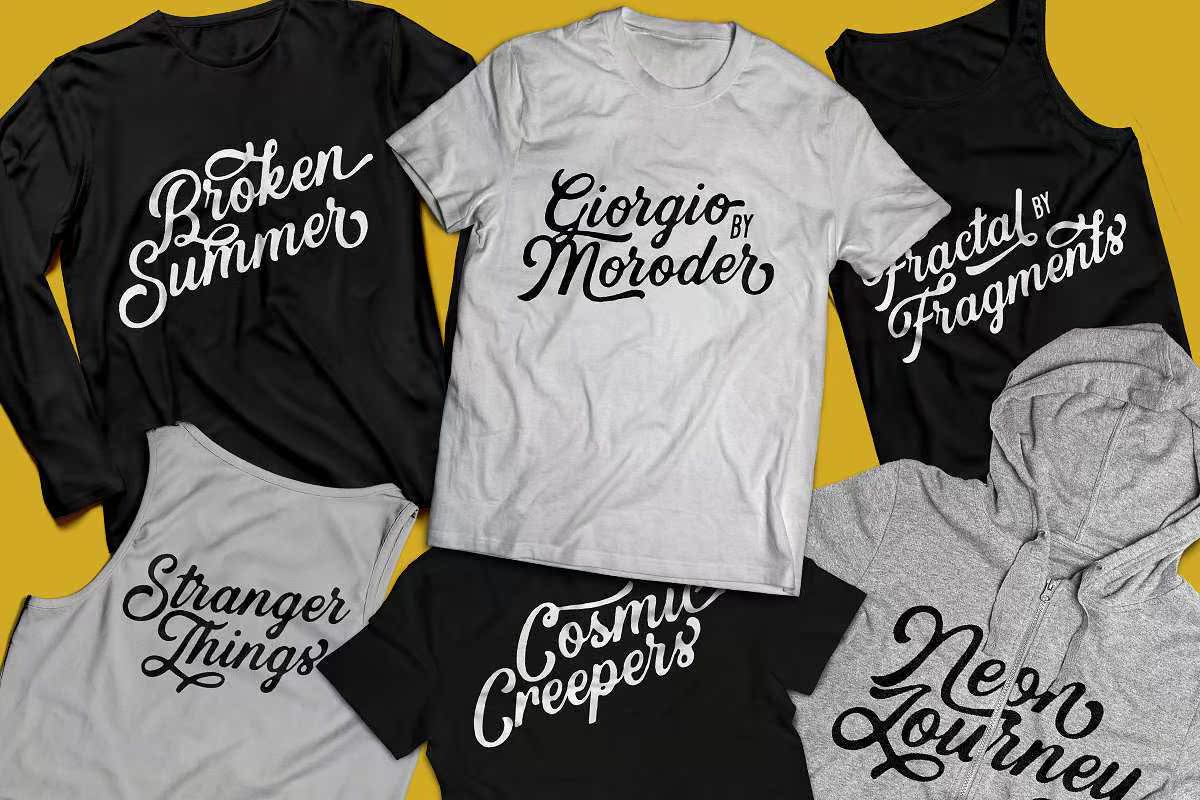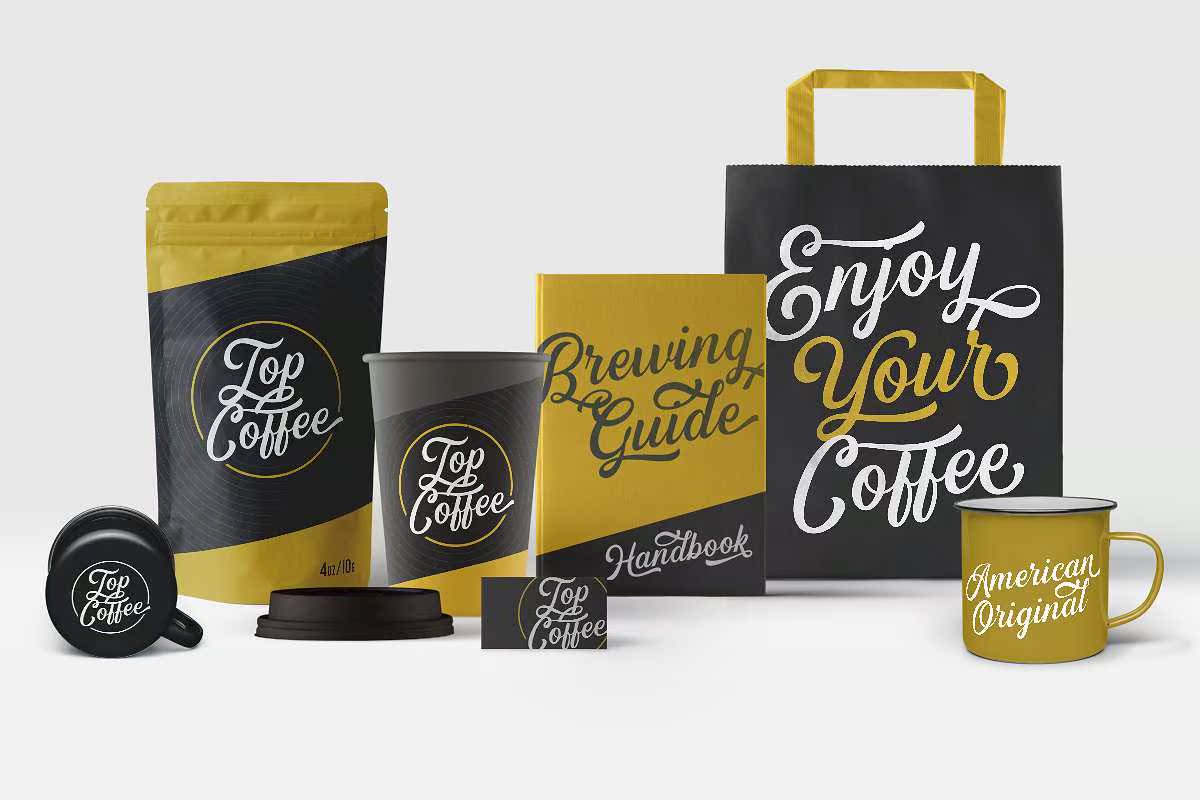
Hipsterious是一款从拥挤的人群中脱颖而出的服装。由两种字体组成,规则而粗糙。特别是在标识、签名、摄影、报价、服装设计和任何设计需求方面,非常完美。通常,任何开放式特征的内容包括连字、风格设置、替换、,ETC还支持多种语言。Hipsterious是一款独立于Crowd的字体。由两种字体组成,既规则又粗糙。特别适合于标识、签名、摄影、引用、装置设计和任何设计需求。通常,任何开放式功能的内容包括连字、风格设置替代等,都可以支持多种语言。